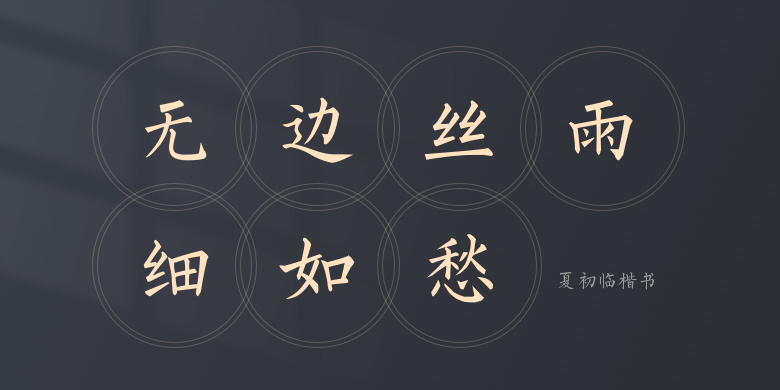
夏初临楷书
夏初临楷书,这款字体结构工整、笔画清晰,兼顾美观与易读性,适用于标题、正文、海报、包装、LOGO 等多种场景。字形优雅稳定,风格百搭耐看,适配日常排版与创意设计,让文字呈现更舒适、更具质感。夏初临楷书一笔一画,皆是细节,以均衡的比例、流畅的线条打造舒适视觉体验,字形端正大气,风格简约现代。无论是商业设计、品牌宣传还是日常排版,都能轻松驾驭,让文字更有格调与力量。夏初临楷书字体下载。